Samy Deluxe »Poesiealbum« [Update]
Tut mir auch leid, liebe EMI, dass ich hier das wunderbare (typografische) Video von Samy Deluxe nicht zeigen kann. Daniel Meyer hat es mir ans Herz gelegt (vielen Dank dafür). Er schreibt: »Für einen Typofan ein leckerer Augenschmaus, das neue Video von Samy Deluxe, falls unbekannt, auf http://www.samy-deluxe.de/ einsehbar. Für die Umsetzung u. a. die ›Typeholics‹ aus Hamburg verantwortlich.«
Ich hätte gerne noch ein bisschen mehr darüber geschrieben, aber dieser kleinkarierte Urheberrechtskrieg zwischen YouTube (die Beklagte; praktisch fürs plattformübergreifende Video-Einbetten), der GEMA (die Klägerin) und den Major-Musikfirmen (die Orientierungslosen) hat mir die Laune verdorben. Vielleicht geht es Samy Deluxe und den Video-Produzenten ähnlich und sie haben deswegen ein Making-of-Video produziert und auf YouTube hochgeladen. Immerhin haben sich das schon 31.000 Samy-Deluxe-Fans angesehen. Ist das jetzt die Zukunft, liebe Musikindustrie, das Angucken wie man Musik und Videos produziert, also der Konsum von Metainformation?
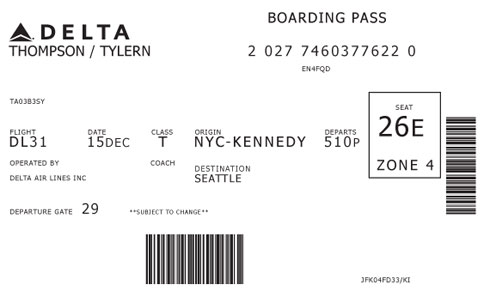Wie fliegen mehr Spaß machen könnte …
Vorher:
Nachher:
Als der Washingtoner Designer Tyler Thompson im Dezember 2009 seinen Kollegen Dustin Curtis in New York City besuchte und wieder zurück nach Seattle flog, ärgerte er sich dermaßen über die Bordkarte, dass er noch im Flieger Ideen für ein Redesign in seinem Moleskine-Buch festhielt. Daraus entstand im Januar die dazugehörige Website Boarding Pass/Fail, auf der sich inzwischen ausgezeichnete Redesign (inkl. Downloads) und Kommentare angesammelt haben. Eine Entdeckung von Spreeblick.
Bitte Provider-Logo nachbessern, Telekom.de
Vor 2 Tagen bekam ich eine SMS von der Telekom auf mein iPhone: »Lieber Kunde, T-Mobile und T-Home wurden in der Telekom Deutschland GmbH zusammengeführt. Die Anzeige in Ihrem Handydisplay ändert sich nach Neustart des Handys in Kürze auf “Telekom.de”.«
Ich war zwei Tage gespannt, wie das wohl gehen soll, 10 Schriftzeichen auf einer Fläche unterzubringen, die bereits mit 8 Zeichen gut gefüllt ist, wobei i und l in Helvetica nur sehr wenig Platz benötigen. Nun ist das neue Provider-Logo da, es heißt kurz ›Telekom‹ statt ›Telekom.de‹ und trotzdem drängeln sich die Buchstaben auf unschöne Art. Sie scheinen auch größer als zuvor.
Fontnäpfchen (17): Telekom-Preisliste [Neu]
So ist es richtig: Tele Grotesk Normal, die Exklusivschrift der Deutschen Telekom in einem Archiv-PDF
So ist es falsch: Ersatzschrift Adobe Sans mit der Metrik von Tele Grotesk, weil diese nicht ins PDF eingebettet wurde (Stand: April 2010)
Das ist es ganz falsch: Fantasieschrift aufgrund eines eigenmächtigen Austauschs der Macintosh-OS-X-Vorschau (Stand April 2010)
[Neu: Da das Thema ›Schriften richtig in PDFs einbetten‹ nicht unwichtig ist, habe ich diesen Beitrag von gestern Abend nicht gelöscht, sondern umgeschrieben. Er war auch nicht prinzipiell falsch, nur ungenau formuliert. So konnten wir alle aus dem Fehler der Telekom lernen. Vielen Dank für die klugen Kommentare.]
Liebe Telekom,
was ist nur mit der »Preisliste für Mobilfunktarife« (Stand April 2010) passiert (PDF)? Statt in der Exklusivschrift Tele Grotesk erscheint die 60-seitige Broschüre auf unseren Bildschirmen in einer Ersatzschrift. Dies passiert, wenn die Originalschrift nicht richtig ins PDF eingebettet wurde. Manche Reader behelfen sich dann mit der Ersatzschrift Adobe Sans, die Macintosh-Programme Vorschau und Safari kommen zu besonders eigenwilligen Lösungen auf Basis einer verunstalteten Helvetica. Bitte korrigieren.
Aufpassen, Bund Deutscher Kriminalbeamter [Update]
Im Juni 2009, auf dem 14. Deutschen Präventionstag in Hannover, stellte der Bund Deutscher Kriminalbeamter (BDK) sein Projekt Web-patrol vor, eine Art 110-Notruf fürs Internet. Das Informationsportal soll zielgruppenorientiert über Fragen der Sicherheit und des Verhaltens im Netz informieren. Parallel dazu gibt es eine kleine Software, über die verdächtige Inhalte direkt an eine »unabhängige Clearingstelle« gemeldet werden können.
Der Hamburger Vielsurfer Hanno Zulla (@hzulla) hat jetzt festgestellt, dass es der BDK möglicherweise mit dem Urheberrecht nicht so genau nehme. Gegenüber Nerdcore fragt er sich, ob der Bund Deutscher Kriminalbeamter möglicherweise Anschluss zur Remix-Kultur suche: »Man vergleiche das Logo auf dem (sehr merkwürdigen) offiziellen BDK-Blog mit diesem Bild des Silver Surfers« (Abbildung oben). Die zitierte Vorlage ist eine Illustration des Bosnischen Künstlers Adi Granov und entstand 2003 für das Cover eines Marvel-Comic-Heftes.
Natürlich wissen wir nicht 100 Prozent, ob sich der BDK vielleicht doch um eine Lizenz für die Konturzeichnung bemüht hat. Nötig wäre sie sicherlich.
[Update: Das Logo wurde inzwischen von der Webseiten des Bund Deutscher Kriminalbeamter entfernt. In diesen PDFs ist es noch zu finden:
Wie schon im Jahr 2009 steht auch in diesem Jahr ein einziges Motiv für die gesamte Berlinale. Auf Sektionsplakate wurde zugunsten einer einheitlichen Kommunikation verzichtet. Ab 26. Januar 2010 wird das Plakat im gesamten Berliner Stadtbild zu sehen sein.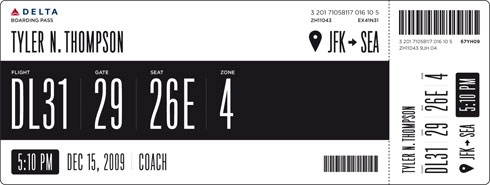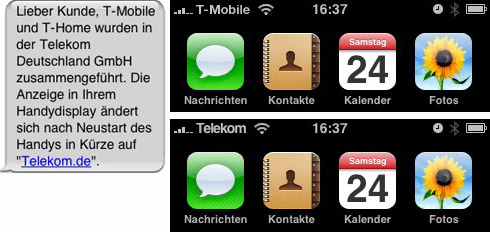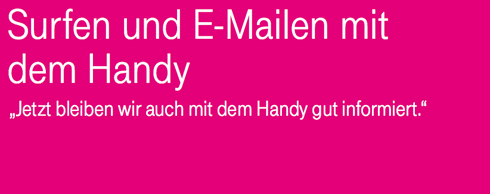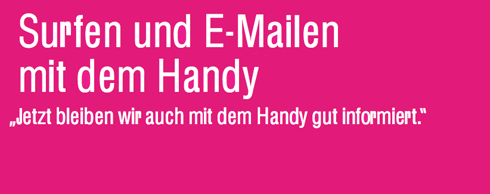